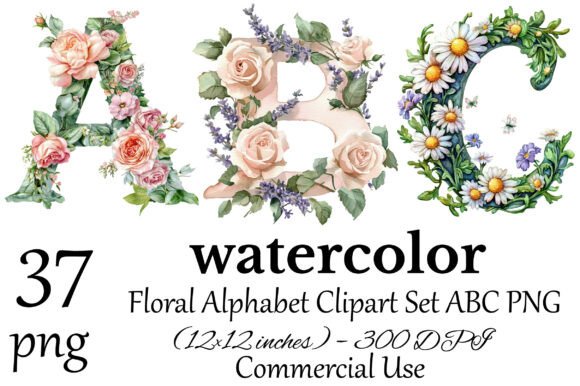
Floral Alphabet Clipart Set ABC PNG
Conçu avec précision, Floral Alphabet Clipart Set ABC PNG offre des vecteurs nets, une typographie fluide et une licence commerciale pour une tranquillité d'esprit.